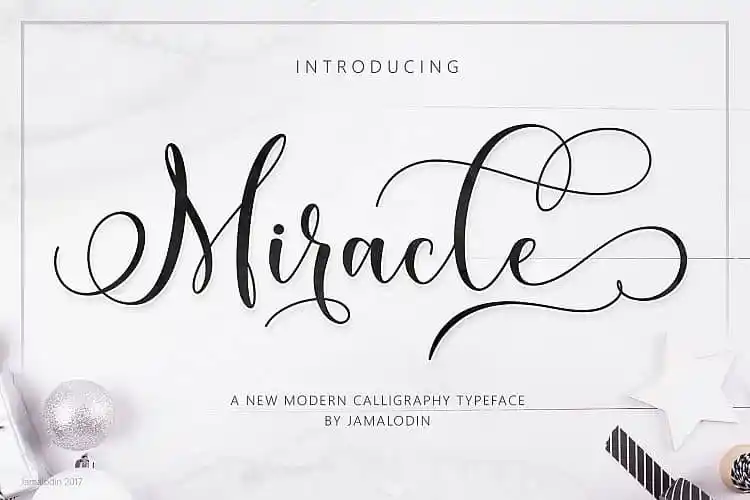
Miracle Calligraphy Font – Download Grátis
Miracle Calligraphy Font é uma elegante fonte para script criada por 178-MC. Ela oferece letras cuidadosamente elaboradas que permitem criar textos perfeitos e atraentes. Esta fonte moderna, com seu estilo de letra, é ideal para diversos projetos, incluindo convites, cartões de agradecimento, quadros, cartões de nome, citações, cabeçalhos de blog, marca, logotipo, moda, roupas, cartas e embalagens. Seja qual for o seu projeto de design, Miracle Calligraphy Font é uma opção perfeita para torná-lo ainda mais atraente e sofisticado.